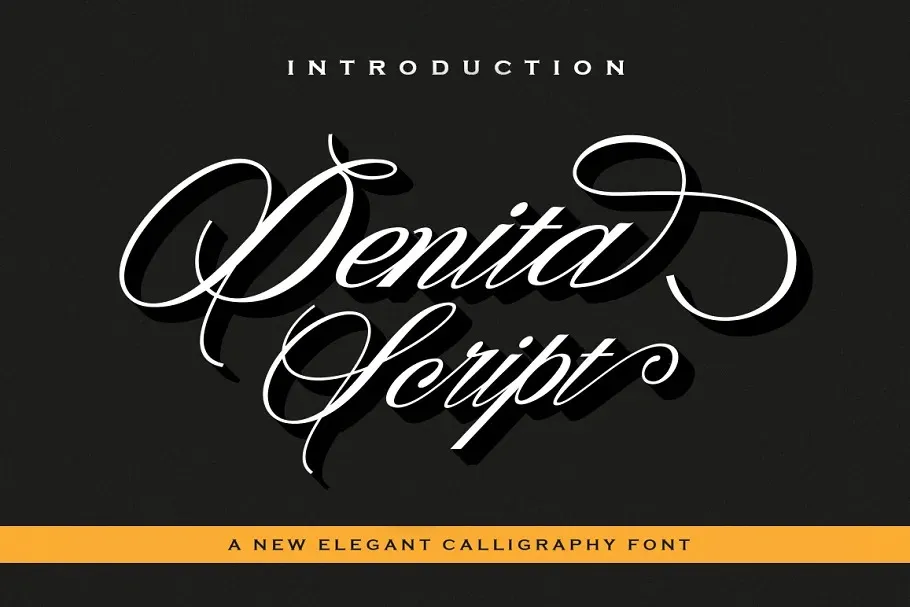
Denita é uma elegante tipografia script moderna desenvolvida para designers buscando um equilíbrio entre personalidade e clareza. Com linhas suaves e limpas, esta fonte deixa um impacto imediato graças aos seus caracteres alternativos estilísticos, tornando-a ideal tanto para projetos comerciais quanto pessoais. Suas alternativas incluem letras iniciais e finais, alterações, ligaturas e suporte multi-língua, tudo isso sob o formato OpenType que oferece uma variedade de opções visuais e funcionalidades. Denita é perfeita para diversas aplicações, como logomarcas, convites de casamento, camisetas personalizadas, cartões de visita, sinalizações, noticiários em jornais ou periódicos, outdoors e até mesmo selos. Suas linhas suaves e harmoniosas tornam-se uma excelente escolha para qualquer projeto que busque um toque sofisticado sem perder o aspecto fresco e moderno associado ao script. Denita é uma fonte de papel com a qual você pode contar em sua paleta, especialmente se estiver buscando um estilo versátil para várias necessidades visuais.